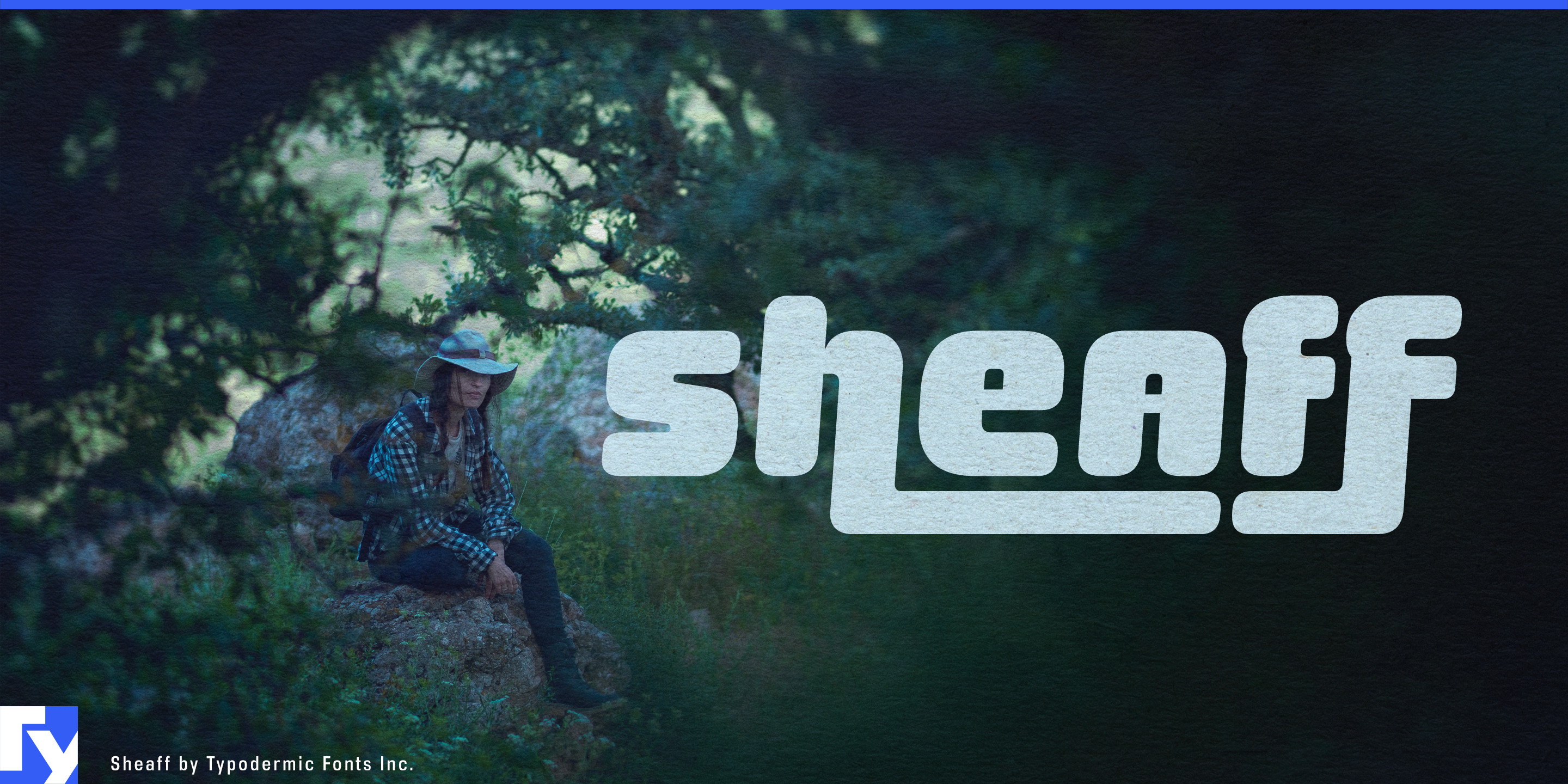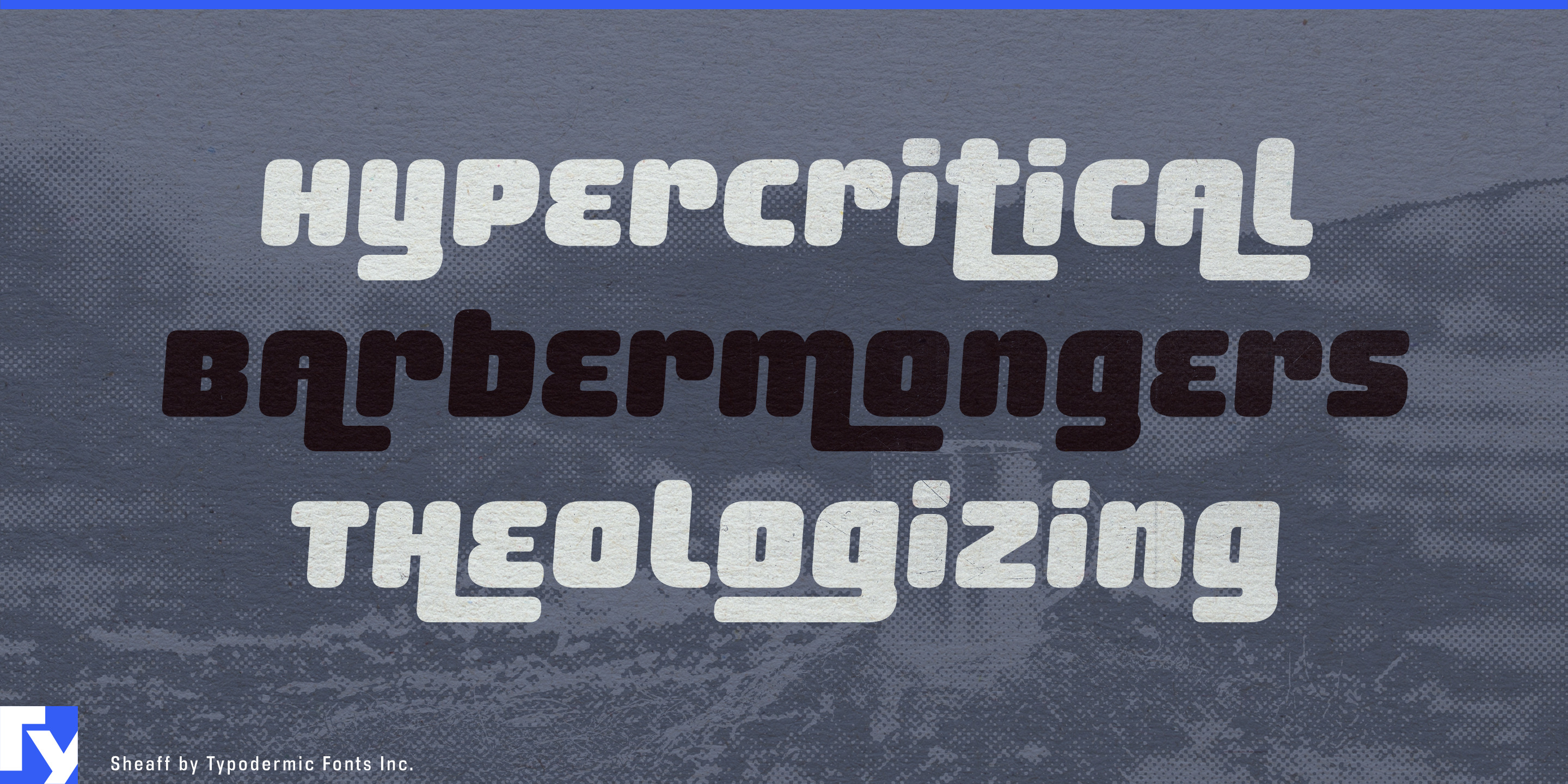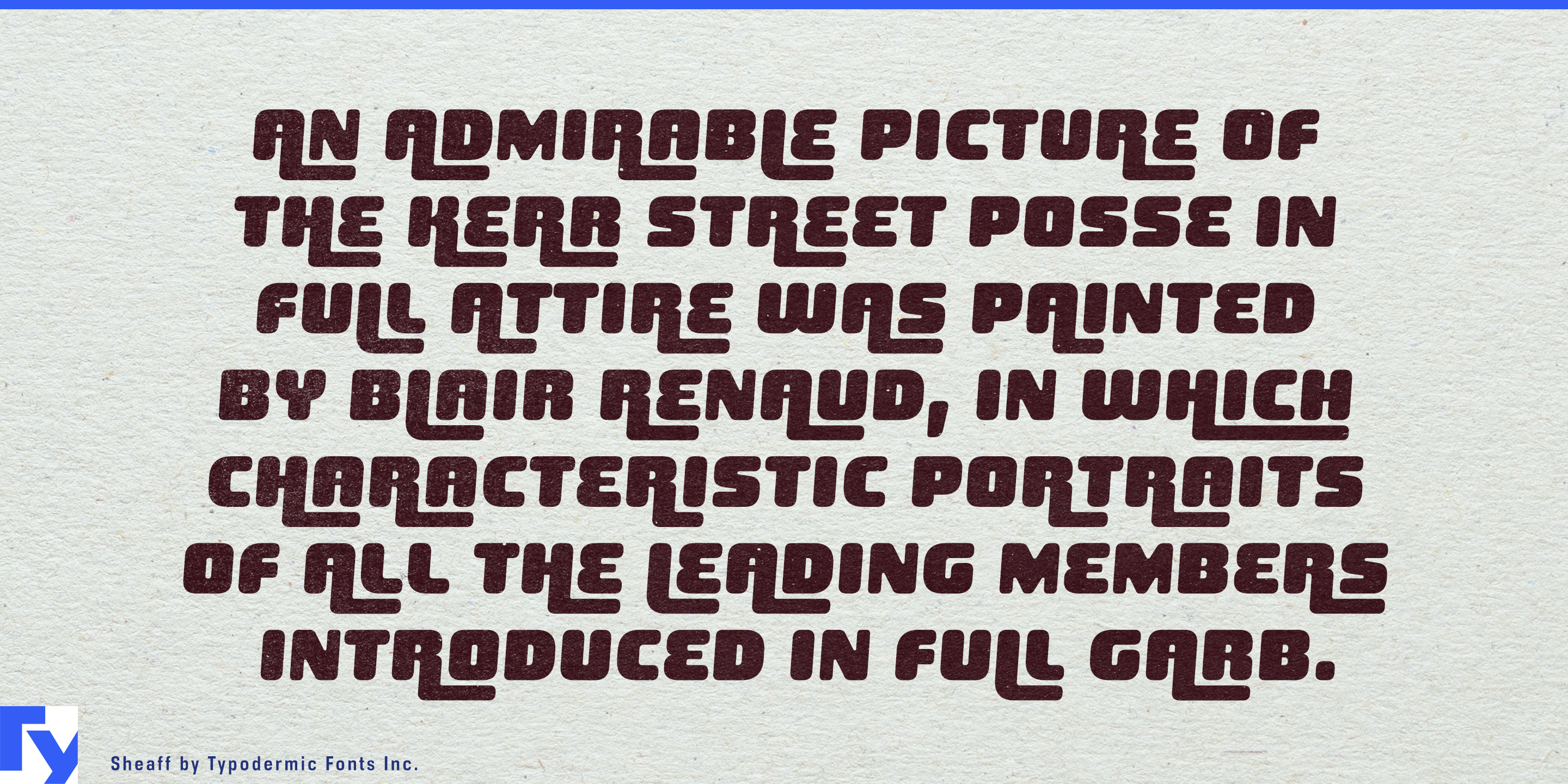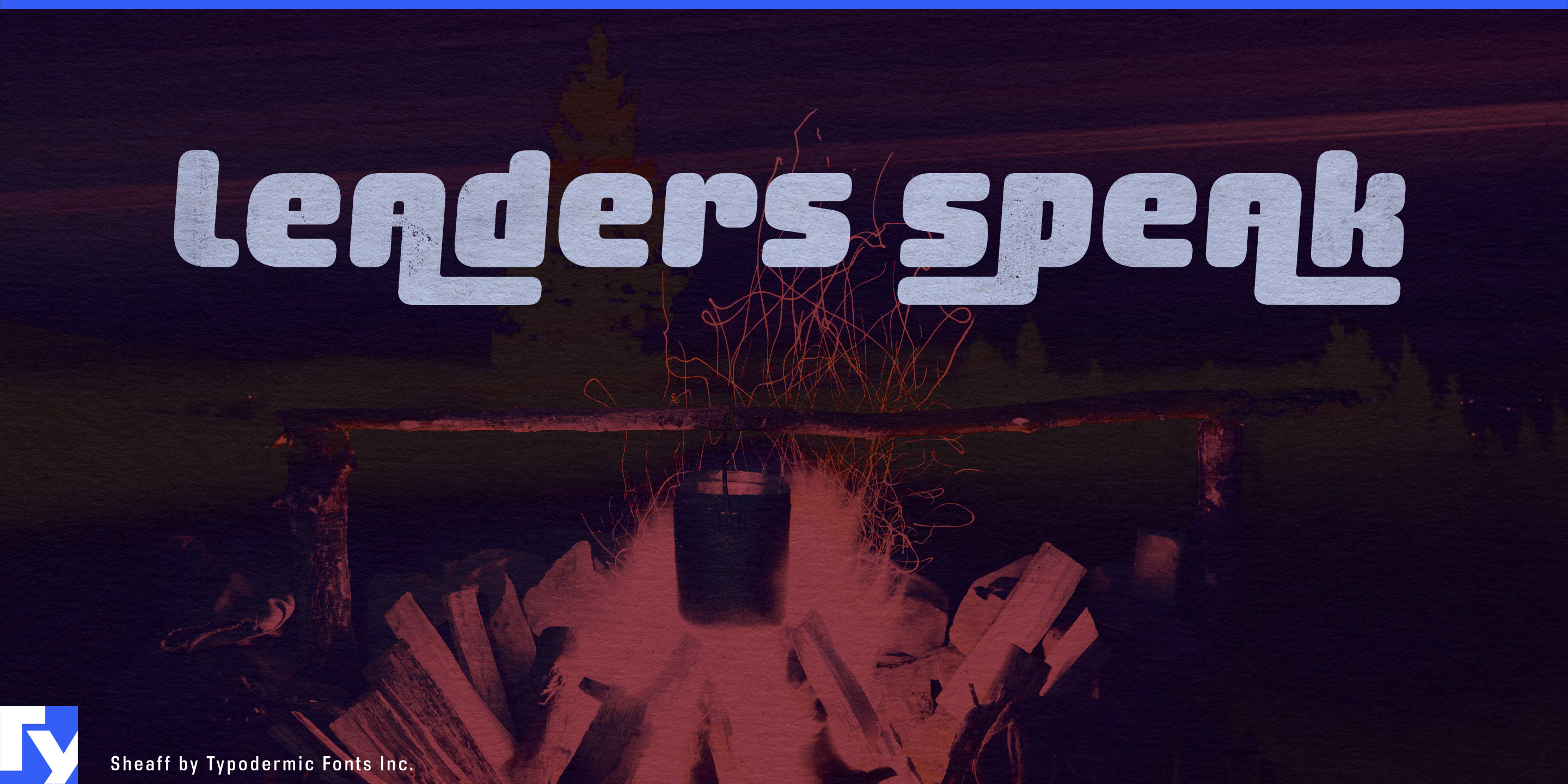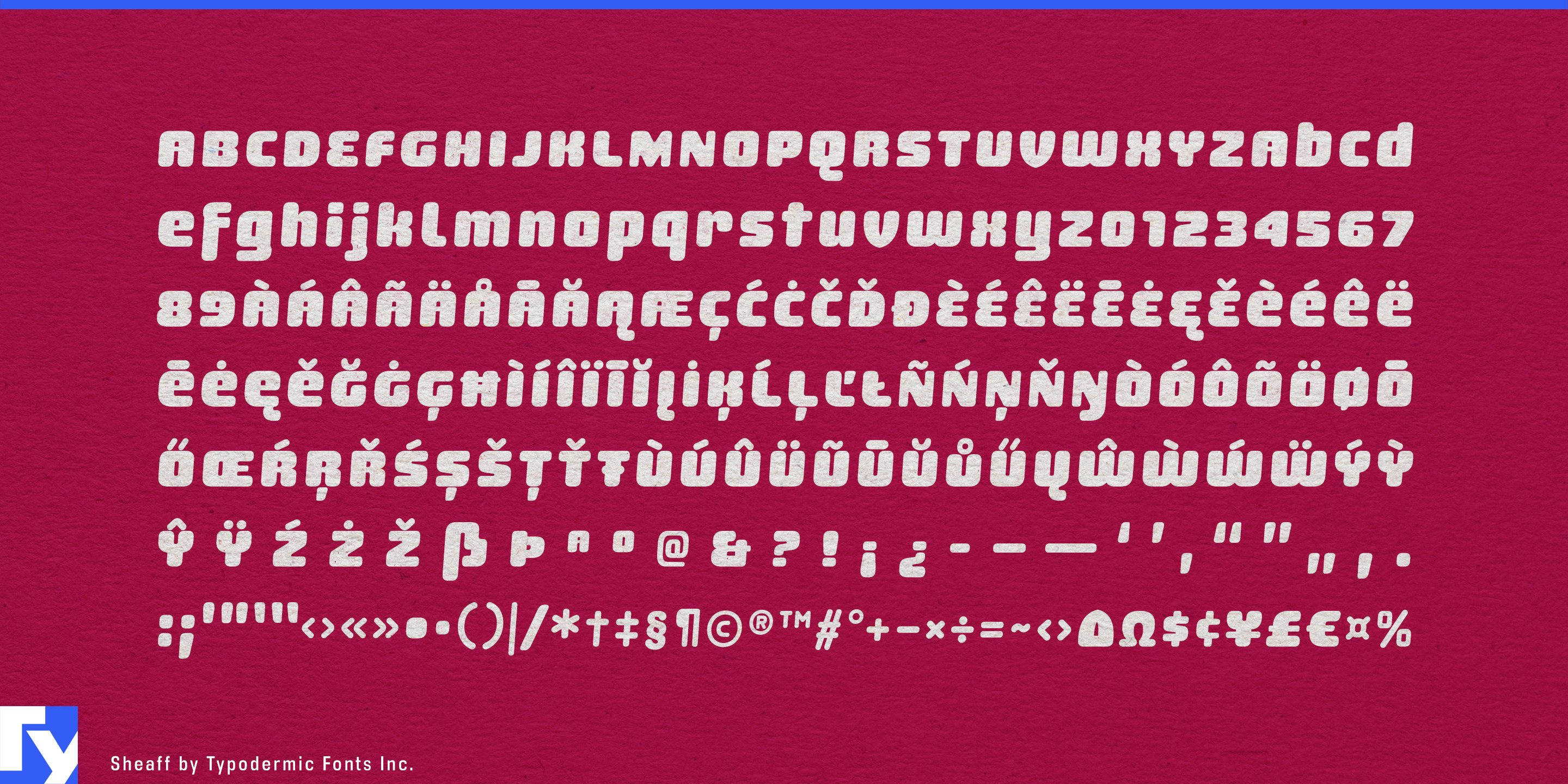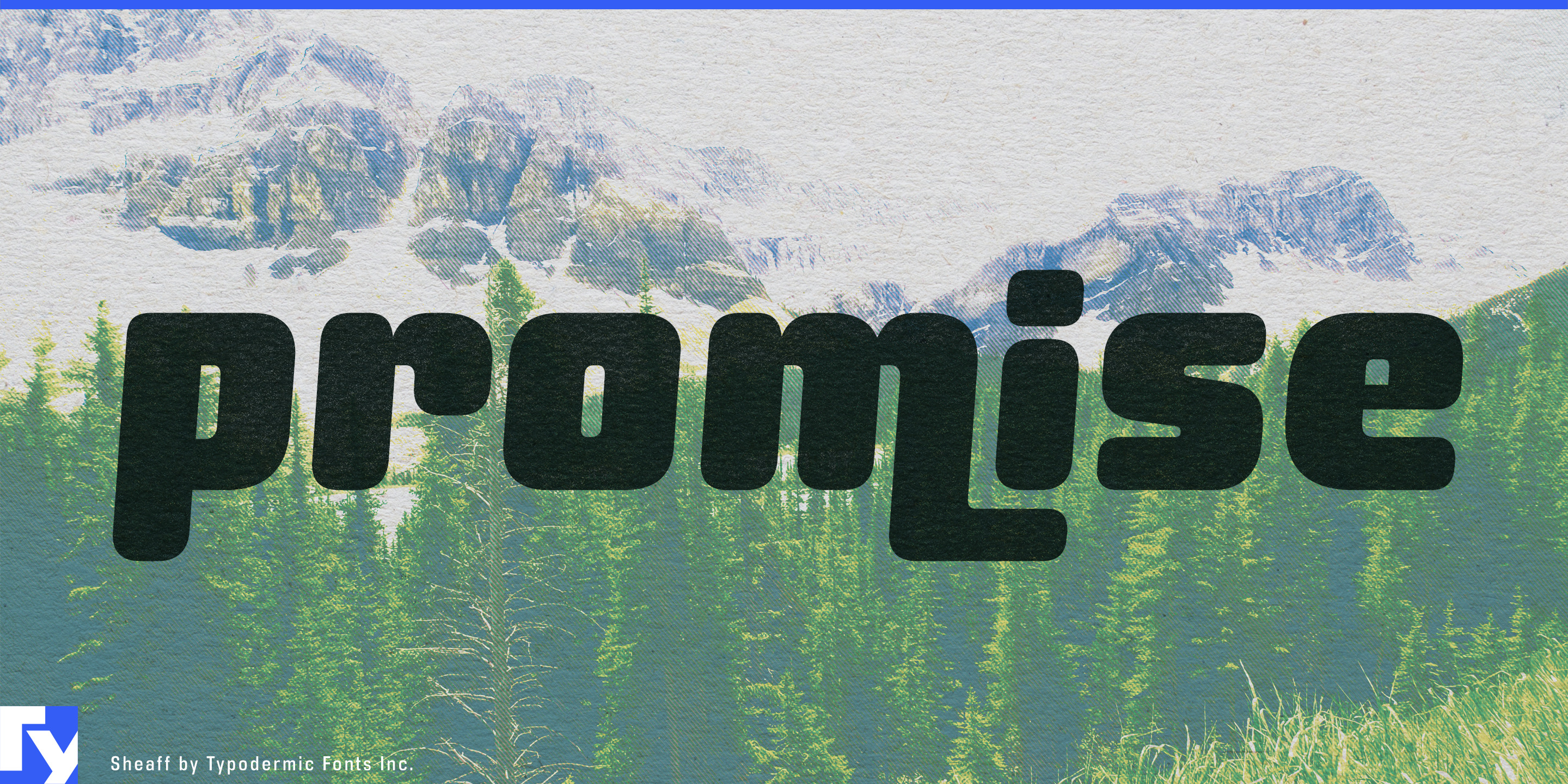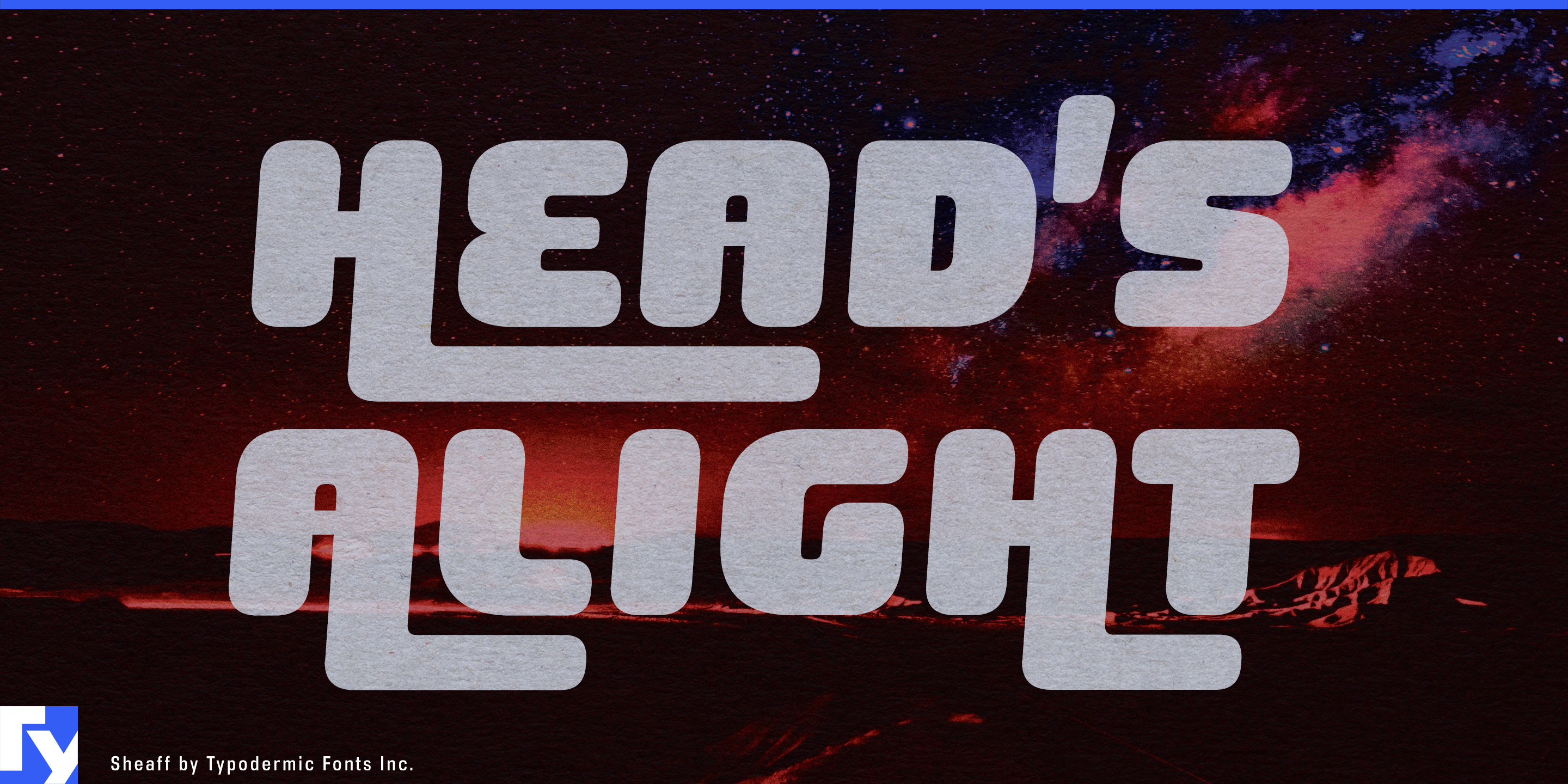
Sheaff
Sheaffは、光沢のある消費者向けのポップな表現、丸いプラスチックの形、明るいパッケージ、文字そのものがグラフィックになる短い名前など、Y2Kの柔らかな側面から生まれました。その構造は2000年前後の語彙とかみ合うディスプレイ文字を組み合わせ、文字を単に横へ並べるのではなく、寄り添わせ、延ばし、下線を作ります。
そのためSheaffは、名前が主役のグラフィックになるときに特に役立ちます。製品名、味の名前、コレクション名、玩具シリーズ名、モデル名を、毎回特注のレタリングを作らなくても、コンパクトなロゴタイプ風の形にできます。つながりや延長線が見えやすい短い見出しで、効果が最も強く出ます。
菓子は自然な用途です。チューインガム、グミ、フルーツ味の噛む菓子、タフィー、マシュマロ製品などの柔らかな菓子は、ふくらんだ明るい色のSheaffの視覚世界をすでに共有しています。主なブランド名をパウチや箱で目立たせ、味の名前、季節限定品、協業企画にも、包み紙、再封できる袋、大袋、棚の展示、自動販売機のグラフィック、発売キャンペーンを通じて同じかみ合う文字の語彙を使えます。
美容・パーソナルケアにも似た機会があります。リップグロス、リップオイル、色付きのバーム、ネイル製品のシリーズ、ボディミスト、入浴用品、一時的なヘアカラー、ポップなスタイリング製品は、短い名前、光沢のあるパッケージ、半透明の素材、頻繁に変わる色や香りに支えられることがよくあります。Sheaffはチューブや箱の製品名、季節のコレクションのタイトル、店頭展示やキャンペーンの中心となる文字を担えます。
玩具や遊具では、同じ形がより直接的な物理的文脈を得ます。人形のシリーズ、収集用フィギュア、スライムや感覚を使う玩具、プレイセット、バランスバイク、三輪車、スクーター、乗用玩具、プラスチック製の滑り台、プレイハウス、水遊び用テーブル、水遊び玩具は、成形プラスチック、ふくらんだ形、明るい色、創作された製品名の世界にあります。Sheaffはパッケージからフレームのデカール、成形バッジ、ステッカー、ホイールカバー、製品へ直接施すグラフィックへ移れます。
Sheaffが登場したころには、Y2Kデザインの柔らかなプラスチック風表現はすでに流行から外れつつありました。2020年代後半から振り返ると、その時期も有用さの一部です。サイバー風の懐古表現に頼らず、当時のバブルガムポップな消費者文化を伝え、かみ合う構造がその参照に実務的な役割を与えます。